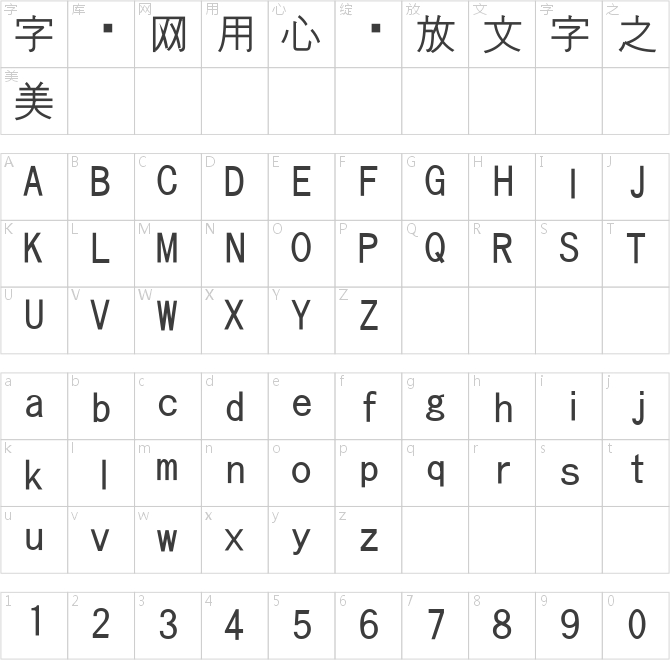
東風(fēng)ゴシック
古川泰之
東風(fēng)フォント(こちフォント)とは様々なフォントを元に古川泰之が開発したフォントファミリである。平成12年(2000年)11月に公開され、平成15年(2003年)10月21日に開発終了となった
東風(fēng)字體(高知字體)是古川泰之基于各種字體開發(fā)的字體家族。 它于2000年11月發(fā)布,開發(fā)于2003年10月21日完成。
東風(fēng)ゴシック字體kochi-gothic-subst字庫是一款讓人賞心悅目、百看不厭的日文字體,適合各類廣告和產(chǎn)品包裝設(shè)計(jì)應(yīng)用,字體大小7.79MB,格式為ttf字體,上傳用戶是西西里,作者/版權(quán)方為古川泰之